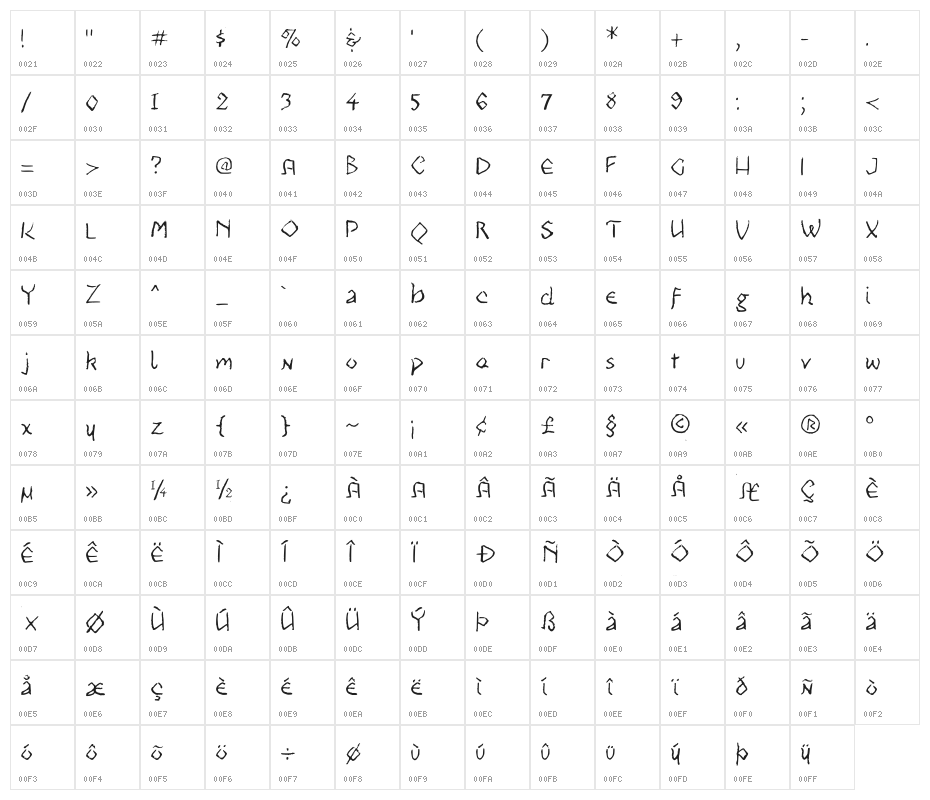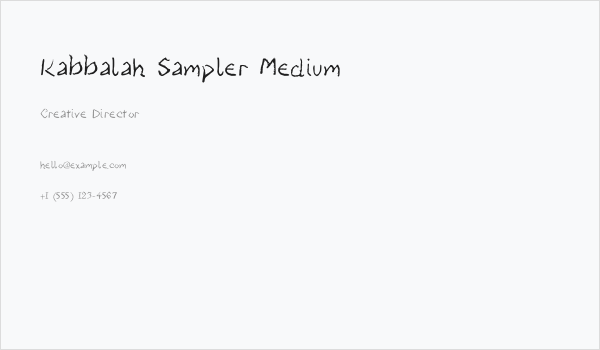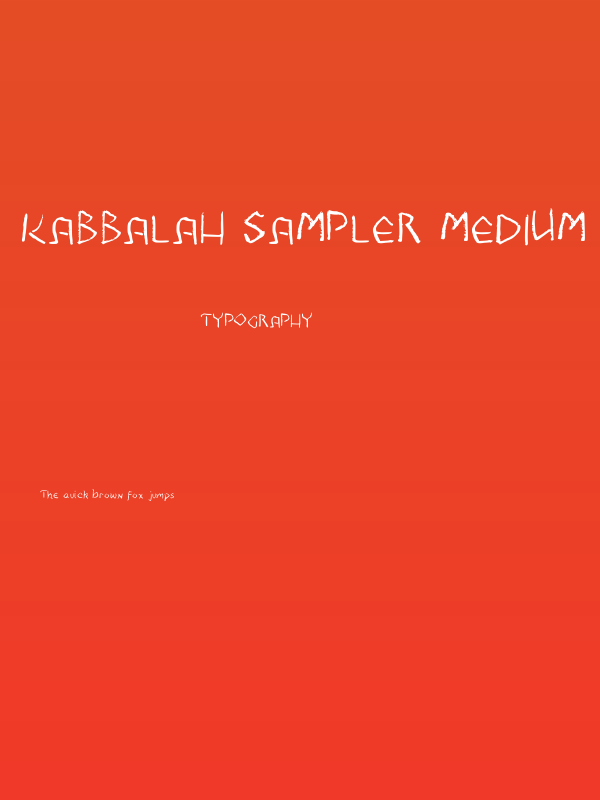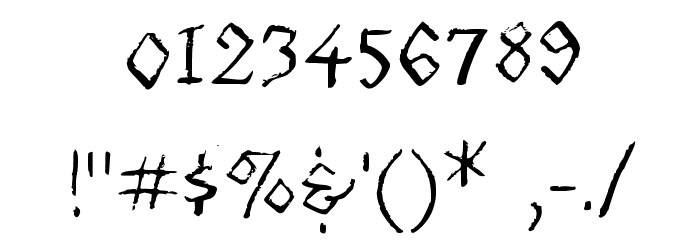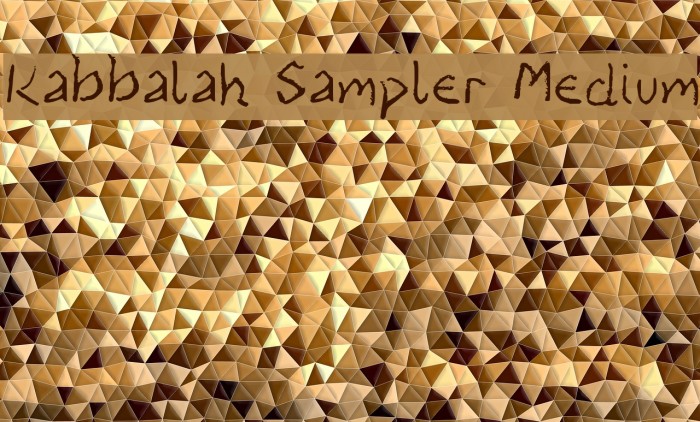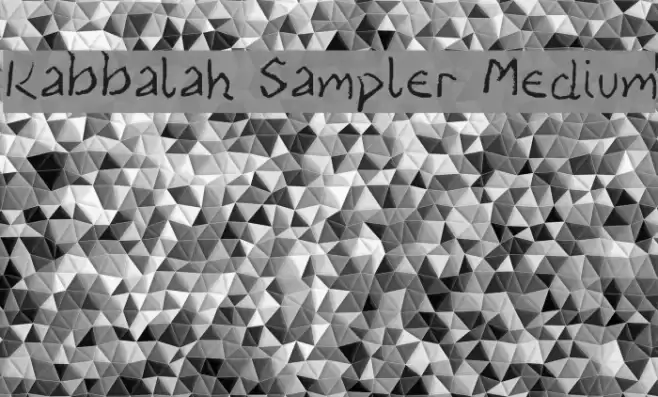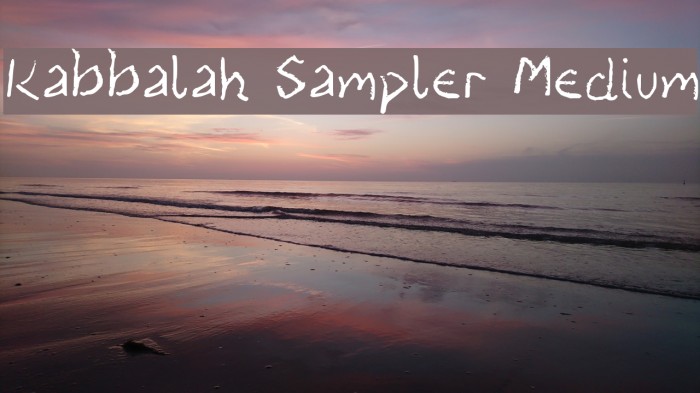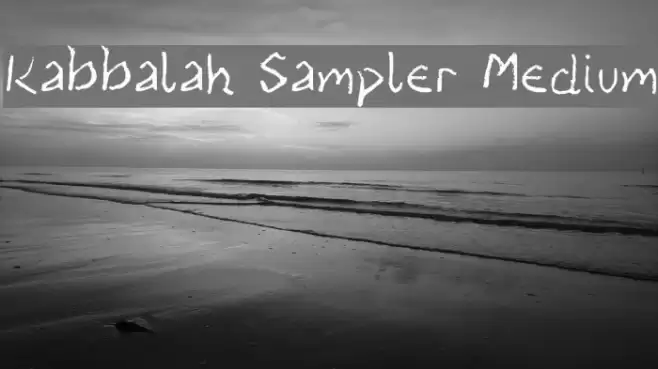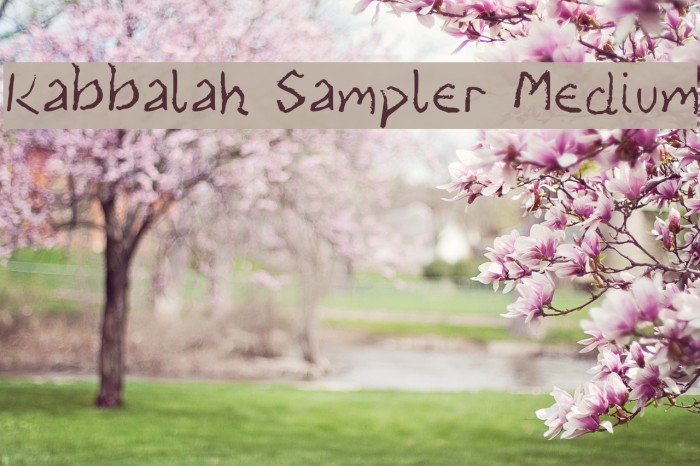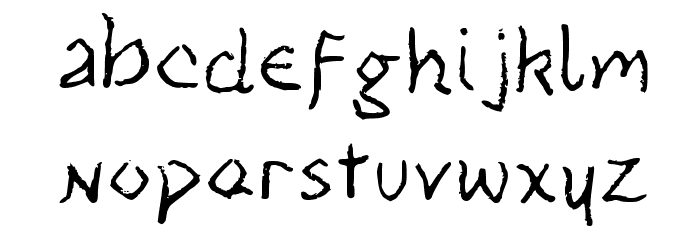
Kabbalah Sampler Medium Font
✎ Calligraphic
| الفئات | Calligraphic |
| حالة الاستخدام | Logos, Headlines, Posters |
| مشاريع مقترحة | Ideal for projects that require a historical or mystical theme, such as book covers, posters, or branding for artisanal products. |